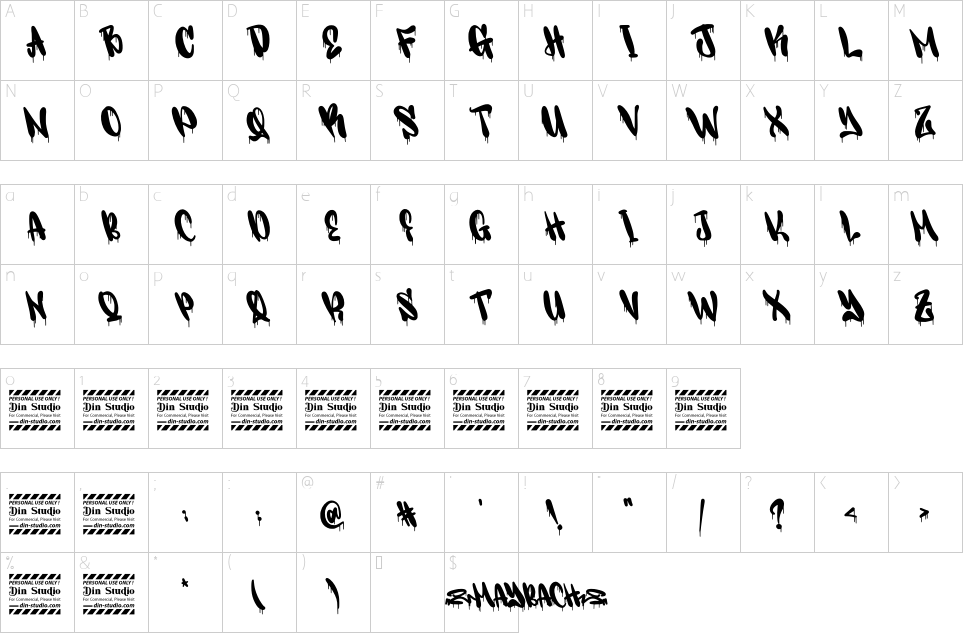
Descubra a beleza e a modernidade da Maybach Font, uma elegante e sofisticada fonte que traz uma atmosfera atraente à sua página web ou projeto de design. Desenvolvida pelo Din Studio, esta fonte gratuita oferece uma ótima combinação de elegância e facilidade de uso. Com apenas um clique, você pode adicionar a Maybach à sua biblioteca de fontes e garantir que seu trabalho seja um destaque. Em um cenário onde as fontes gratuitas podem ser escassas, o Maybach oferece um toque de sofisticação sem custos adicionais. Através de sua página, você pode facilmente descobrir e baixar a Maybach para Windows e Mac, permitindo que você crie projetos profissionais sem limitações. Desde o título até as subtítulos, ou até o texto em geral, a Maybach é uma escolha inteligente para aqueles que buscam um equilíbrio entre elegância e praticidade.